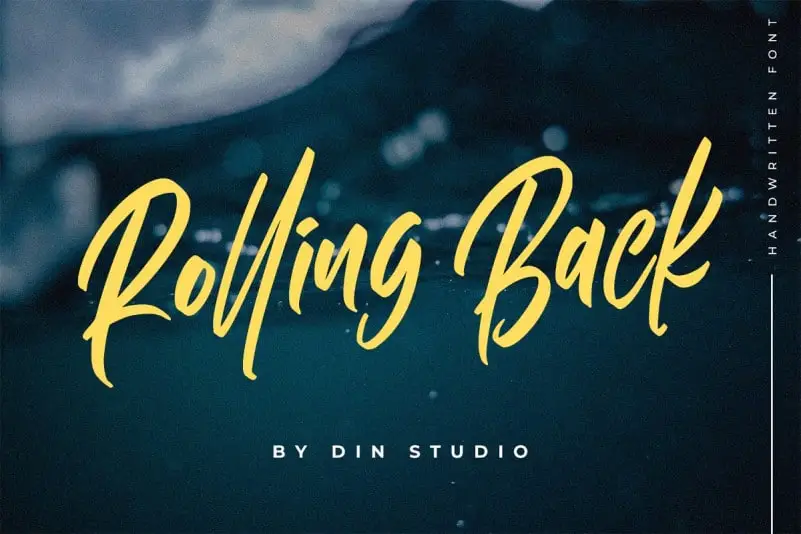
Rolling Back Script Font – Download Grátis
A fonte Rolling Back Script é uma opção perfeita para aqueles que buscam um estilo elegante e sofisticado sem sacrificar a amabilidade de uma fonte feita à mão. Disponível na categoria de Script Fonts, essa fonte foi criada pelo designer Din Studio com base em escrita naturalmente humana. Ideal tanto para uso em logotipos quanto em posters, Rolling Back possui um ar elegante e casual que se adapta a qualquer tipo de design. Ideal para adicionar um toque refinado a aplicações como logomarcas, cartazes, identidades visuais, mensagens ou qualquer outro meio que valoriza uma expressão sofisticada. Com suas linhas finas, femininas e estilizadas, Rolling Back é perfeitamente adaptável à variedade de tamanhos e ambientes gráficos. Suave e amigável, ela oferece uma combinação única de elegância e facilidade, tornando-a não apenas recomendada para uso em um vasto leque de aplicações, mas também indispensável.